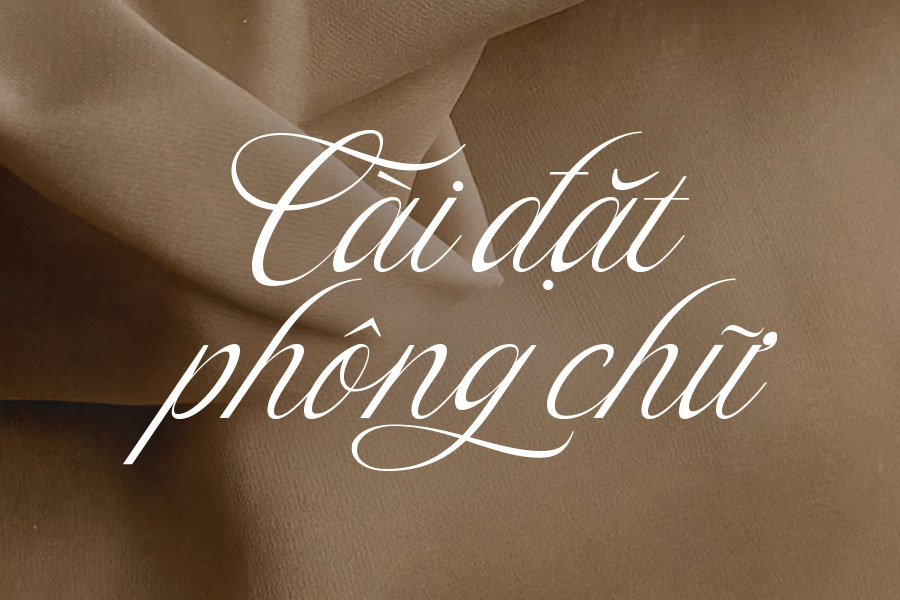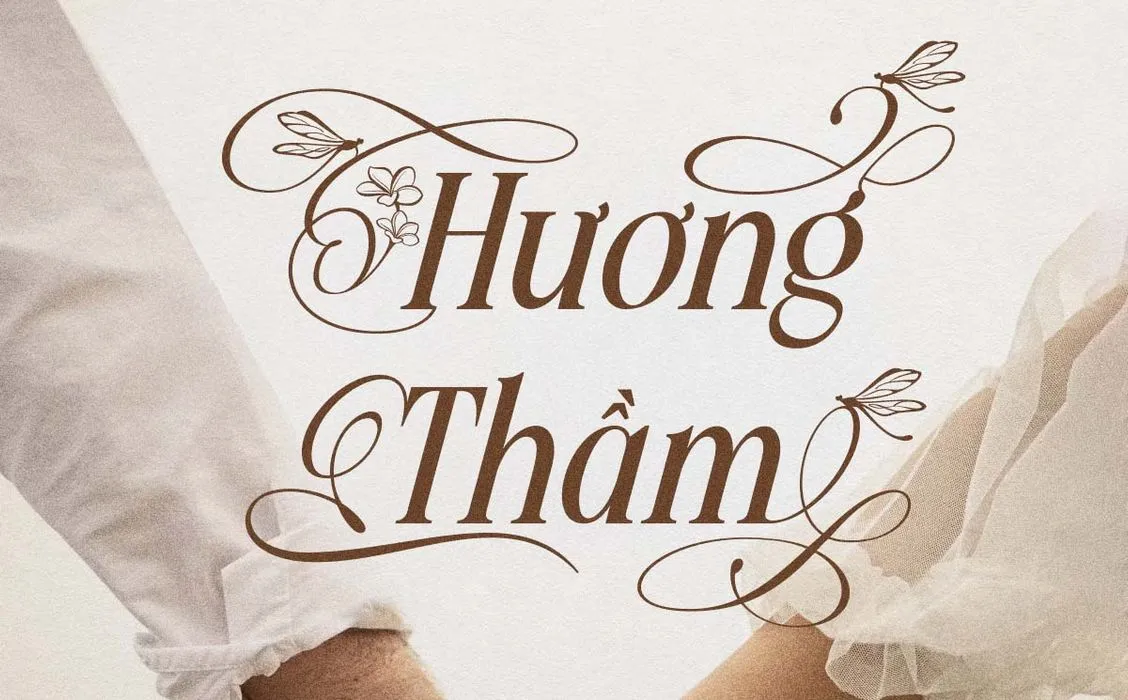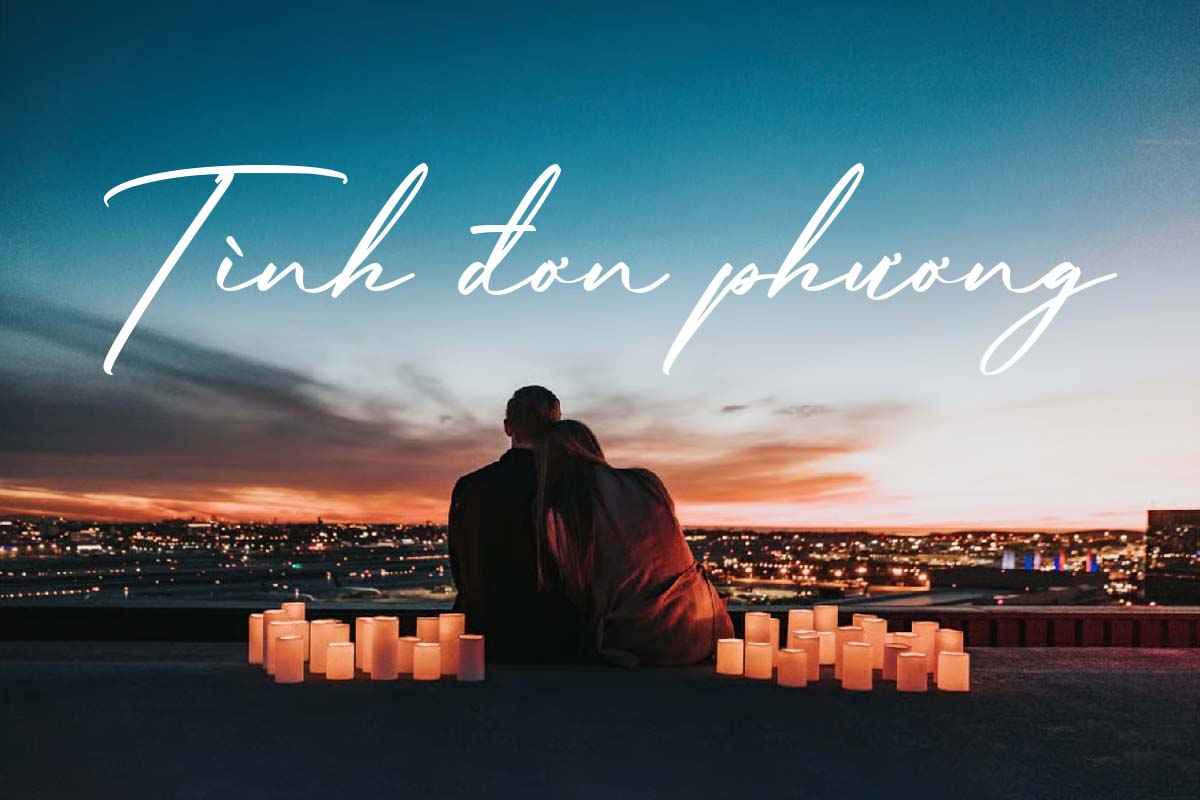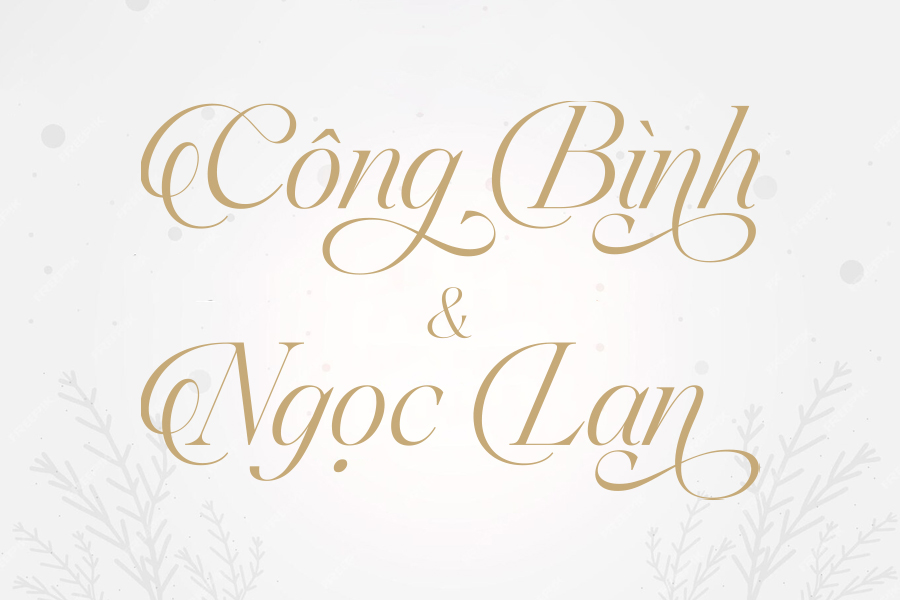
Bộ 15 font thiệp cưới Việt hóa đẹp nhất 2025 – từ script mềm mại đến serif thanh lịch, giúp bạn thiết kế thiệp mời sang trọng và cảm xúc.
Tải ngay bộ 15 font chữ thiệp cưới Việt hóa tuyệt đẹp – từ font viết tay mềm mại đến serif thanh lịch. Bộ sưu tập hoàn hảo giúp bạn tạo nên những tấm thiệp mời cưới sang trọng, tinh tế và đầy cảm xúc.
Thiệp cưới không chỉ là lời mời, mà còn là dấu ấn đầu tiên thể hiện gu thẩm mỹ của cặp đôi. Một font chữ phù hợp sẽ truyền tải trọn vẹn sự lãng mạn, thanh lịch và trang trọng của ngày trọng đại.
Trong bài viết này, Fontdep.vn gợi ý 15 font thiệp cưới Việt hóa đẹp nhất 2025, giúp bạn dễ dàng chọn được kiểu chữ hoàn hảo cho tấm thiệp hạnh phúc của mình.
Font Chữ Thiệp Cưới: Chìa Khóa Cho Sự Lãng Mạn Và Sang Trọng
Font Chữ Thiệp Cưới Là Gì?
Font chữ thiệp cưới (Wedding Fonts) là những kiểu chữ được thiết kế riêng để sử dụng trong các ấn phẩm cưới hỏi như thiệp mời, menu, bảng hiệu, backdrop hoặc logo cưới.
Những font này thường thuộc nhóm Script (viết tay), Serif thanh lịch hoặc Sans Serif tối giản, nhằm truyền tải cảm xúc lãng mạn, trang trọng và tinh tế.
Đặc điểm nổi bật:
- Tính cảm xúc cao: Nét chữ mềm mại, uyển chuyển (Script) hoặc thanh mảnh, tinh tế (Serif).
- Trang trọng: Gợi cảm giác cổ điển, lịch thiệp, phù hợp với các dịp trọng đại.
- Việt hóa hoàn hảo: Hiển thị đầy đủ các ký tự có dấu, giúp nội dung thiệp và tên cô dâu chú rể được thể hiện trọn vẹn.
- Phối hợp linh hoạt: Thường kết hợp giữa một font Script nổi bật và một font Serif hoặc Sans Serif dễ đọc.
Ứng Dụng Nổi Bật Trong Thiết Kế Cưới
Font chữ thiệp cưới có tính ứng dụng rất đa dạng, không chỉ giới hạn trong thiệp mời:
- Thiệp mời chính: Dùng font Script cho tên cặp đôi và font Serif/Sans Serif cho phần nội dung.
- Ấn phẩm đi kèm: Menu, thẻ cảm ơn, thẻ tên bàn tiệc.
- Trang trí sự kiện: Bảng welcome, backdrop, bảng chỉ dẫn.
- Branding cá nhân: Logo cưới, chữ ký cá nhân, in ấn trên quà tặng hoặc hộp quà lưu niệm.
Danh Sách 15 Font Chữ Viết Thiệp Cưới Việt Hóa Đẹp
Dưới đây là bộ sưu tập 15 font chữ thiệp cưới lãng mạn, thanh lịch, đã được Việt hóa hoàn chỉnh và tuyển chọn kỹ lưỡng bởi Fontdep.vn, lý tưởng cho mọi phong cách thiệp cưới.
1. Font viết tay BL BeyongPerfection Việt Hóa – phong cách Script hiện đại
Font BL BeyongPerfection mang phong cách script hiện đại pha calligraphy, mềm mại nhưng vẫn sang trọng. Kiểu chữ này lý tưởng để in tên cô dâu chú rể trên thiệp cưới, thiệp mời, hoặc thiết kế logo thời trang – mỹ phẩm. Mỗi nét chữ đều toát lên sự tinh tế và cao cấp, tạo cảm giác sang trọng ngay từ ánh nhìn đầu tiên.
2. Font BL Hazle Gelia Việt Hóa – lãng mạn và mềm mại cho thiệp cưới
Font BL Hazle Gelia thuộc nhóm script cao cấp, nổi bật với đường nét mềm mại, uyển chuyển và giàu cảm xúc. Các chi tiết swash và flourish tinh tế giúp font trở nên sang trọng, tự nhiên và gần gũi. Đây là lựa chọn lý tưởng cho thiệp cưới cao cấp, thiệp cảm ơn hoặc logo thương hiệu tinh tế.
3. Font trang trí TH Meillona Việt Hóa – Serif thanh lịch cho wedding design
Font TH Meillona là kiểu serif nghiêng độc đáo, mang vẻ đẹp thanh lịch và lãng mạn lấy cảm hứng từ thiên nhiên. Các chi tiết hoa, lá và chuồn chuồn tạo nên nét trang trí nhẹ nhàng nhưng tinh tế, giúp thiết kế trở nên cao cấp. Phù hợp cho thiệp cưới nghệ thuật, lời mời sang trọng hoặc logo thời trang – mỹ phẩm.
- Tác giả gốc: Ni Nyoman Puspa Dewi
- Việt hóa bởi: Font TH
4. Font BL Brenelsa Việt Hóa – calligraphy thanh thoát, sang trọng
BL Brenelsa mang phong cách calligraphy tinh tế, với những đường nét uốn lượn mềm mại và đầy nghệ thuật. Font thể hiện sự thanh thoát, nhẹ nhàng, rất thích hợp cho thiệp cưới, thư mời, logo cao cấp hoặc bao bì thời trang. Sự kết hợp giữa duyên dáng và sang trọng khiến BL Brenelsa luôn nổi bật trong mọi thiết kế.
- Tác giả gốc: Jamaluddin
- Việt hóa bởi: Font BL
5. Font chữ ký TH Bramostia Việt Hóa – tinh tế và nghệ thuật
TH Bramostia là font chữ ký tinh tế, mô phỏng nét viết tay mềm mại và tự nhiên. Font hỗ trợ tiếng Việt đầy đủ, có nhiều ligature và alternate giúp dòng chữ trông mượt mà và cảm xúc hơn. Rất lý tưởng cho thiệp mời cưới, logo cá nhân, watermark hay tiêu đề blog mang phong cách sang trọng.
- Tác giả gốc: Rantau
6. Font chữ ký TH Maistoray Việt Hóa – hiện đại và thanh lịch
Kết Luận
Trong thiết kế, việc chọn đúng font chữ là yếu tố quan trọng để tạo nên sự chuyên nghiệp và khác biệt.
Với 15 font chữ thiệp cưới Việt hóa trong bài viết này, bạn đã có trong tay bộ sưu tập hoàn hảo cho mọi dự án mang phong cách lãng mạn, thanh lịch và ấn tượng.
Dù là thiệp mời, menu hay bảng welcome, chỉ cần chọn đúng font, hiệu ứng thẩm mỹ sẽ tăng lên đáng kể.